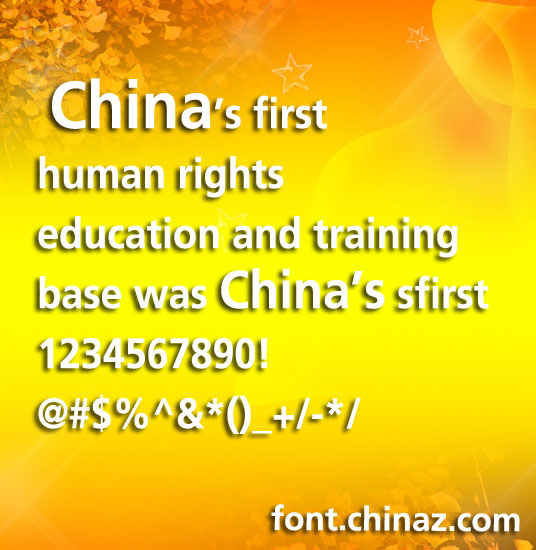
Frutiger系列字体
简介:Frutiger是一款西文无衬线字体,由瑞士设计师Adrian Frutiger设计。这个新字体初命名为Roissy,于1975年完成,并在当年在机场使用。设计师Frutiger的目标是制作一个新的无衬线字体,保留Univers的整洁美观的特点,并加入Gill Sans字体有机元素,因此形成了Frutiger清晰可读性。